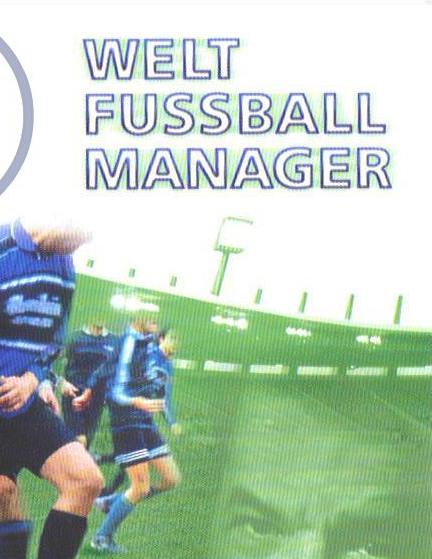
Schriftart zu CD Fußball MNGR
Ich suche die Schrift vom PC Game Welt Fußball Manager. Ich hab die Schrift von der CD Hülle mal eingescannt.
und gibts die auch in dieser Outline-Fassung?
Nicht, dass ich wüsste. Sieht so aus, als ob man die Outline durch einen »Schatten nach innen« erzeugt hat. Die wirkt etwas unsauber an den Eckpunkten.